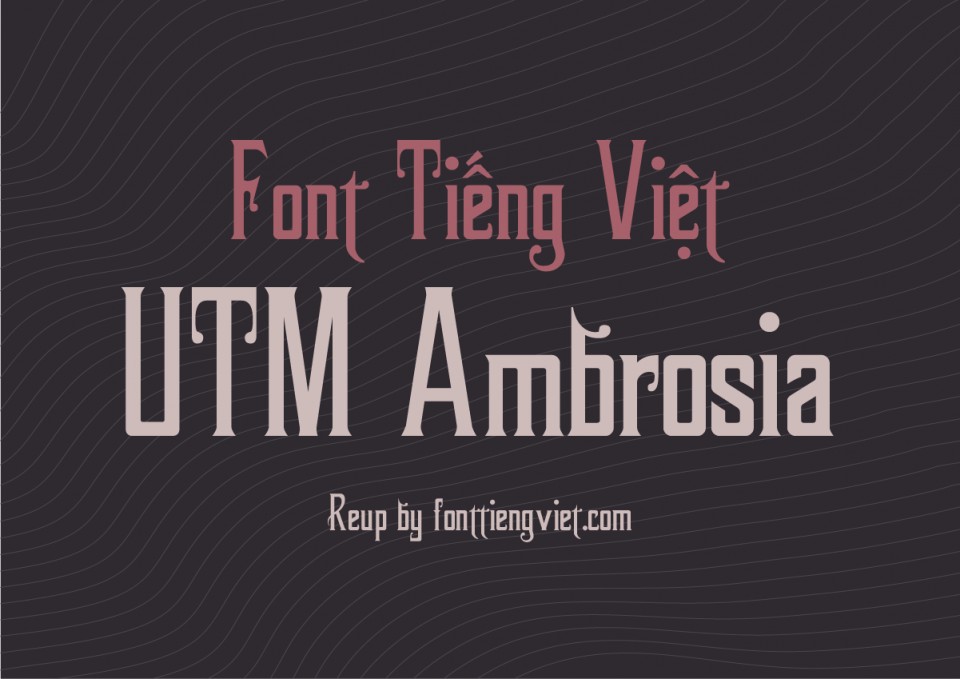
Font tiếng việt UTM Ambrosia
Giới thiệu về bộ Font tiếng việt UTM Ambrosia
Trong thế giới đồ họa hiện đại, việc lựa chọn một bộ Font Chữ phù hợp đóng vai trò quyết định đến tính thẩm mỹ của sản phẩm. Font Miễn Phí luôn là ưu tiên hàng đầu của các bạn học sinh và giáo viên khi thiết kế bài giảng hay làm báo cáo. Đặc biệt, Font tiếng việt UTM Ambrosia nổi lên như một lựa chọn hoàn hảo nhờ phong cách mềm mại nhưng không kém phần trang trọng. Đây là bộ font đã được việt hóa hoàn chỉnh giúp người dùng gõ tiếng Việt có dấu mà không bị lỗi hiển thị, rất phù hợp cho các dự án sáng tạo đòi hỏi sự tinh tế và tỉ mỉ trong từng nét chữ.
Những ưu điểm nổi bật của Font tiếng việt UTM Ambrosia
Thiết kế thanh lịch và đa dụng
Font tiếng việt UTM Ambrosia sở hữu những đường nét uốn lượn nghệ thuật, mang đậm hơi thở cổ điển pha lẫn hiện đại. Bộ font này cực kỳ hữu ích khi ứng dụng vào thiết kế thiệp mời, bìa sách hoặc các tiêu đề trình chiếu PowerPoint trong nhà trường. Sự cân đối giữa các nét thanh và nét đậm giúp văn bản trở nên dễ đọc và thu hút thị giác ngay từ cái nhìn đầu tiên.